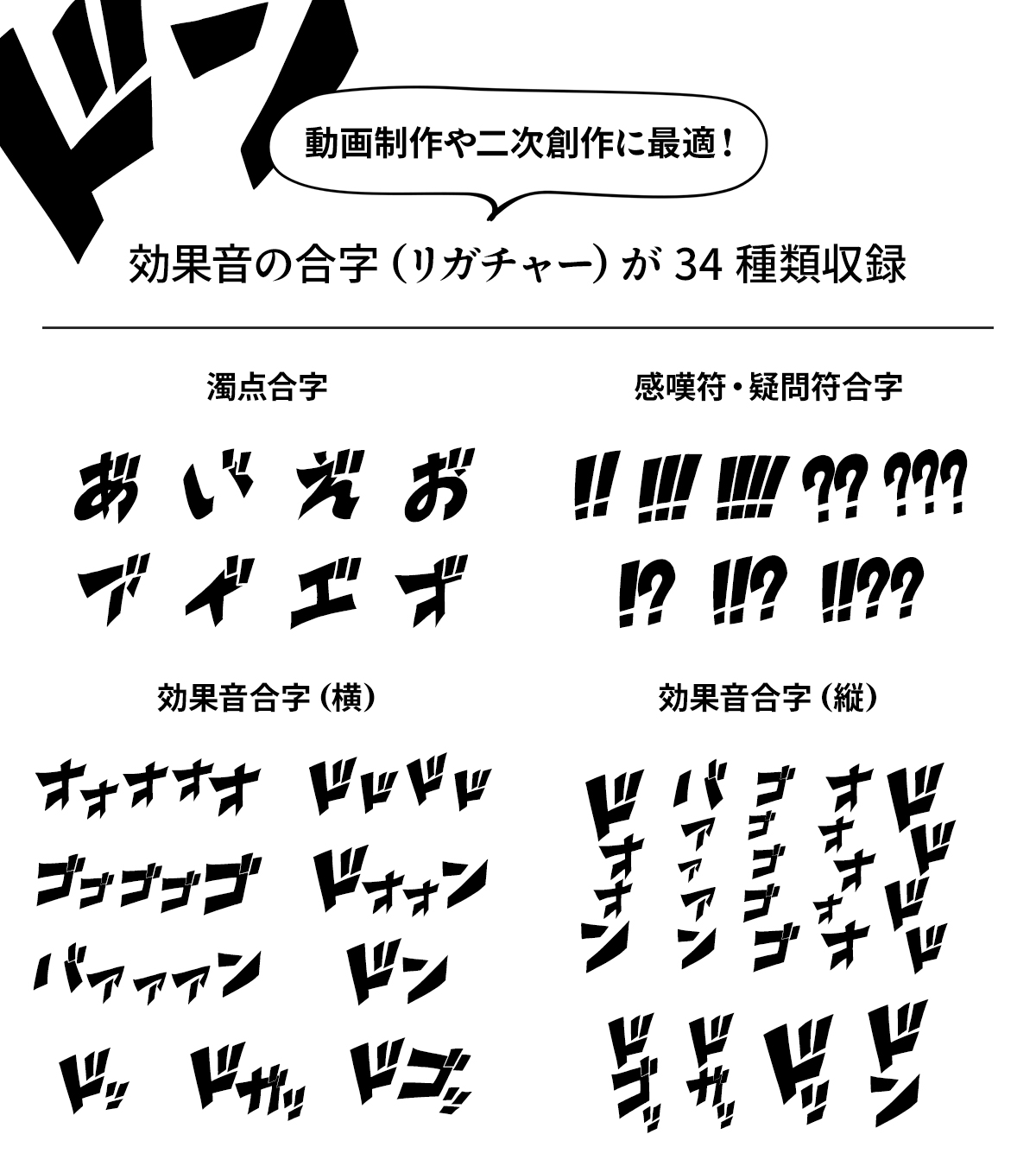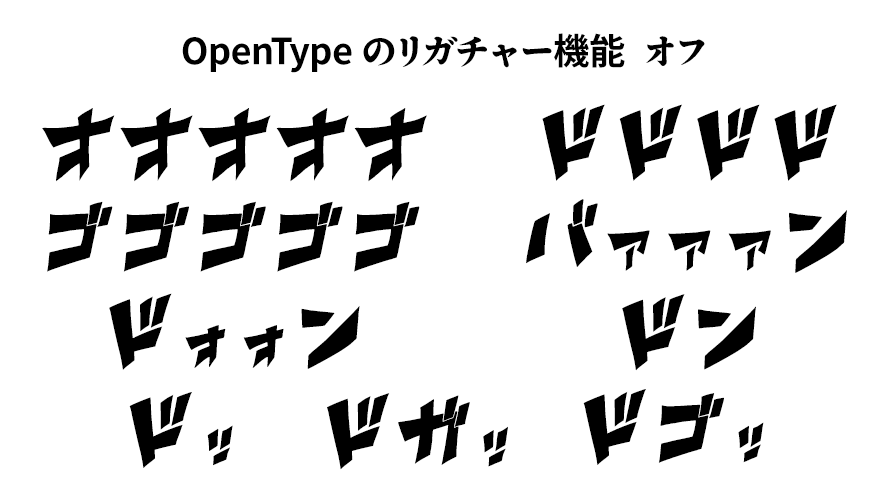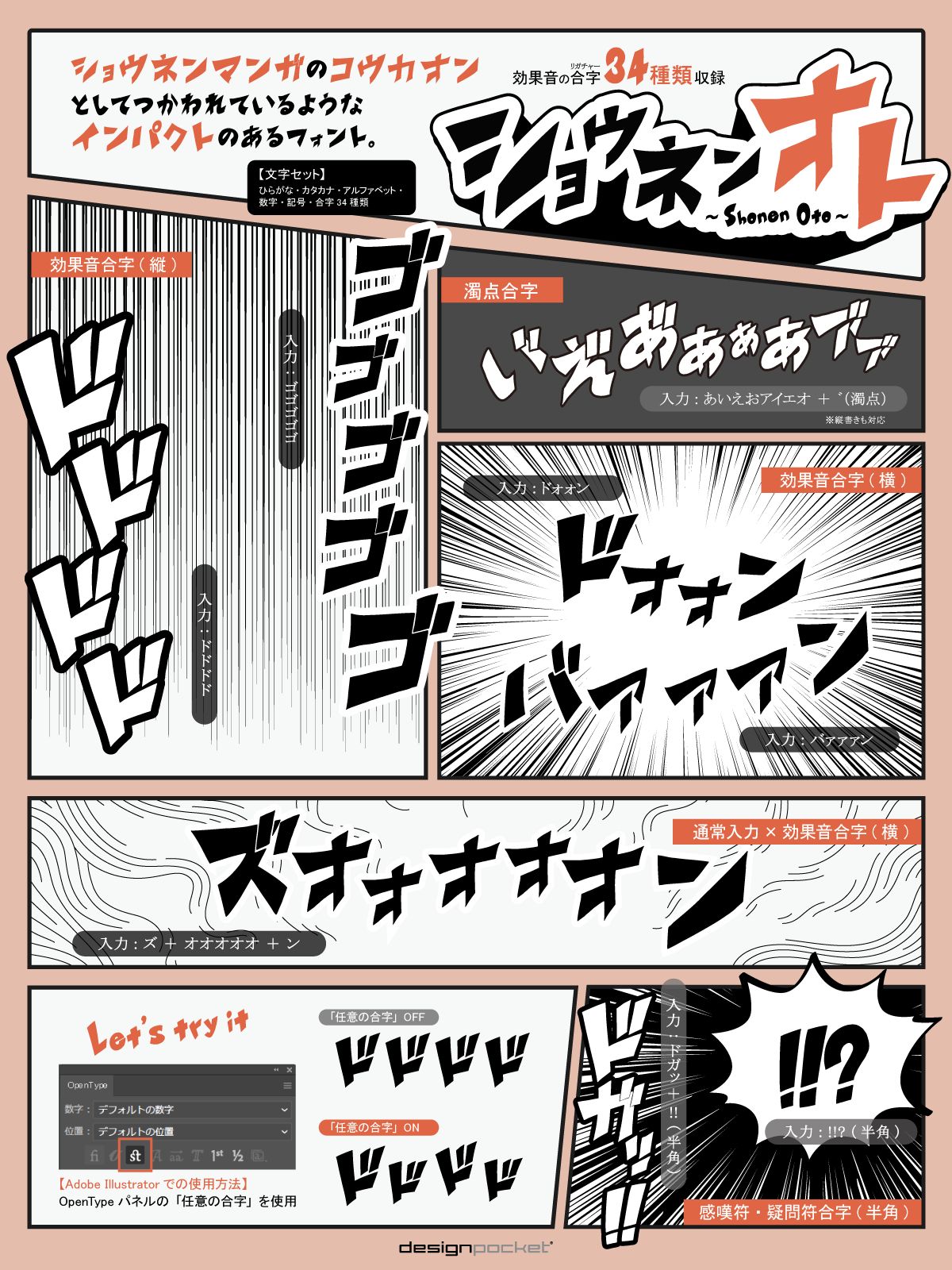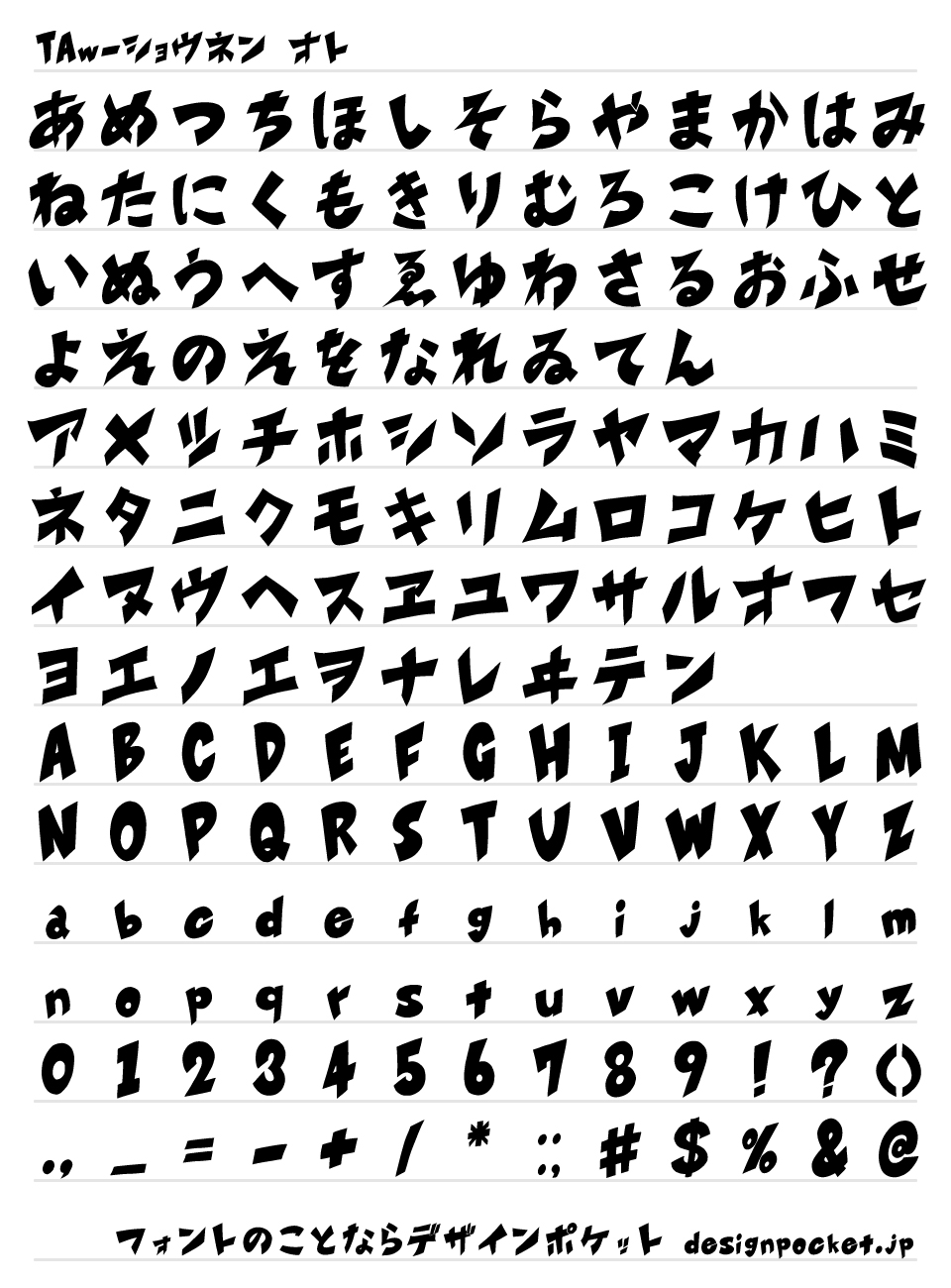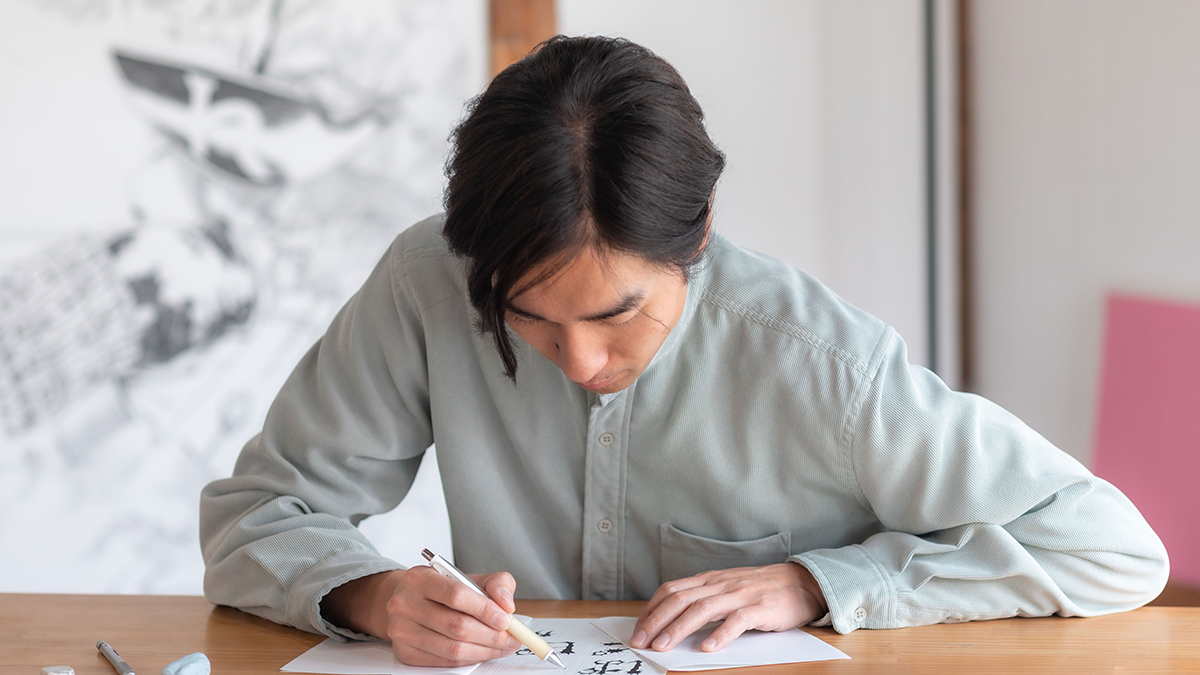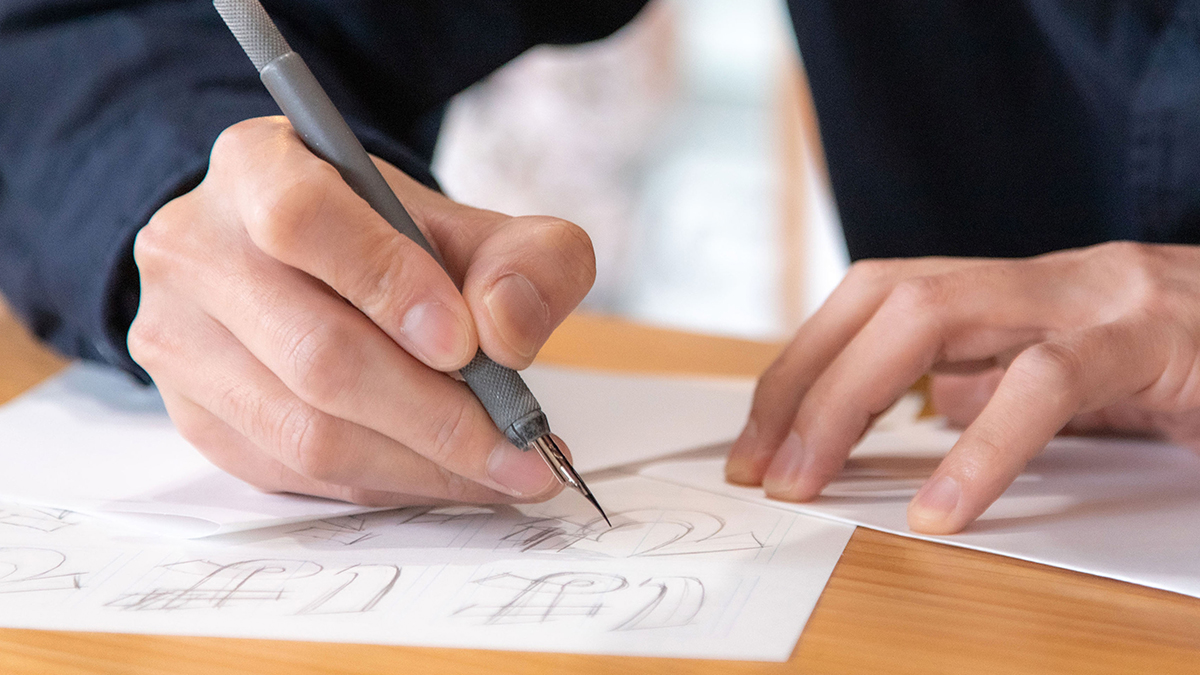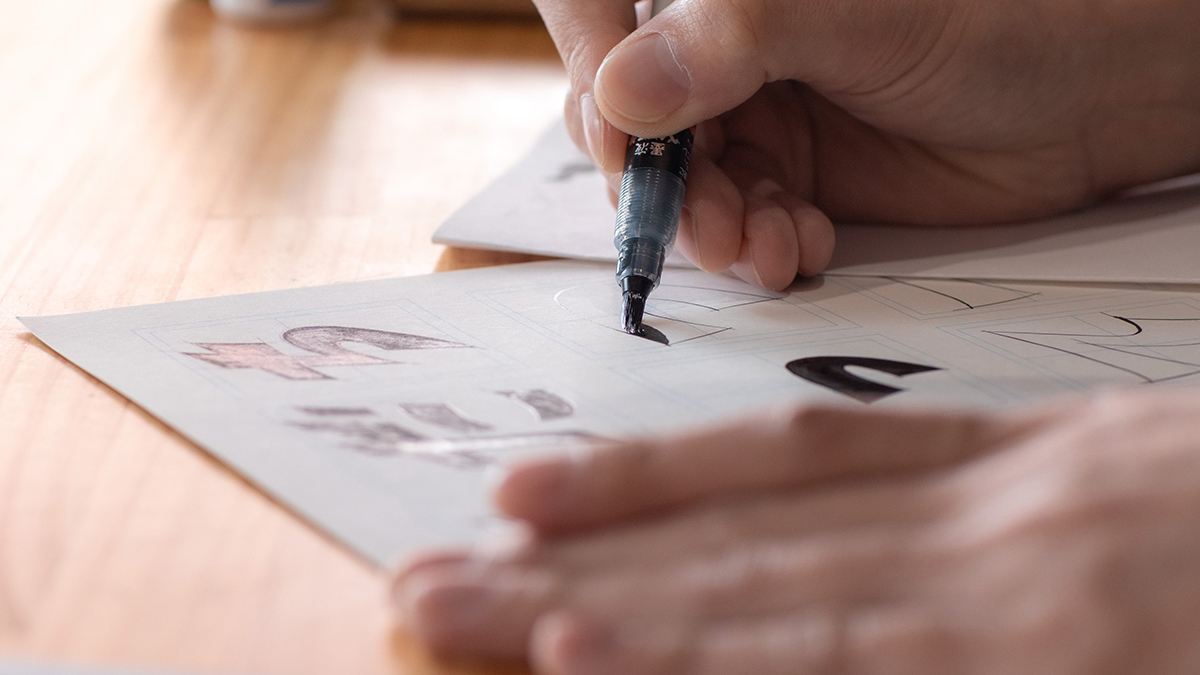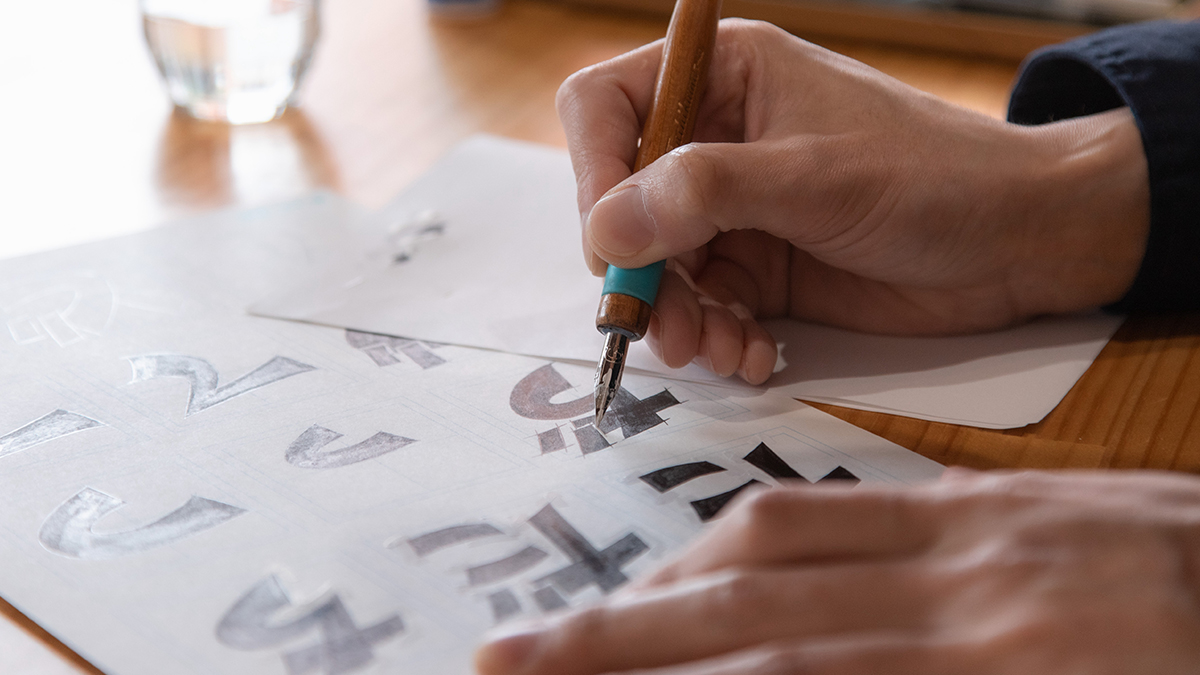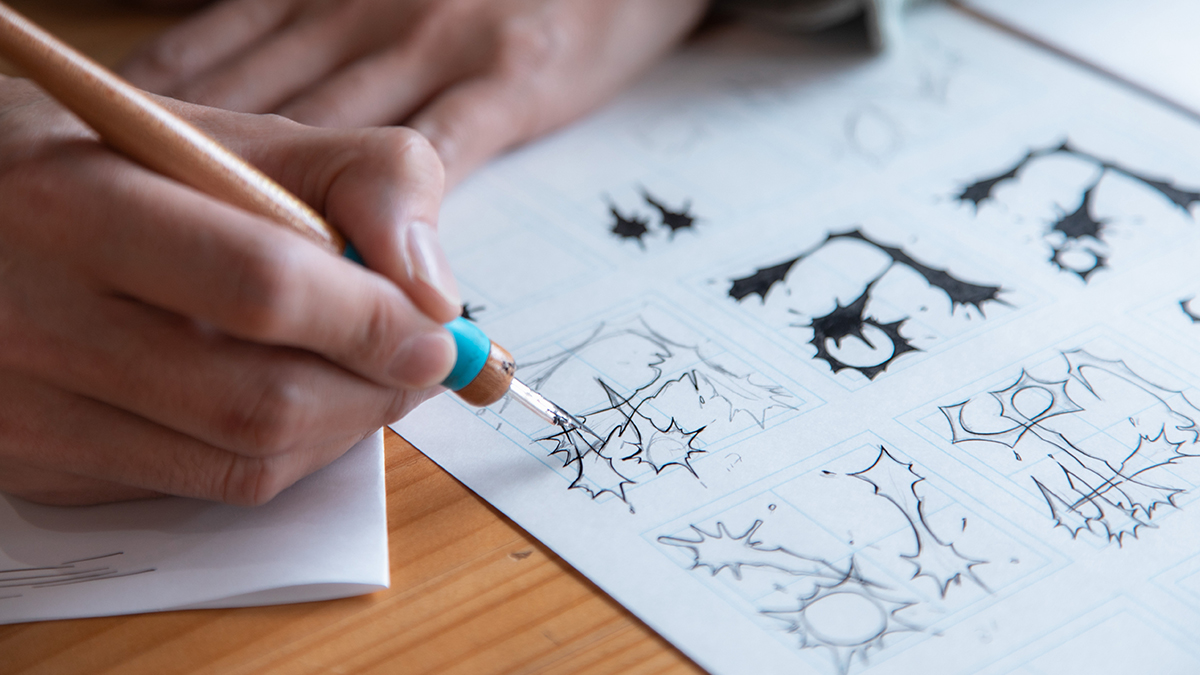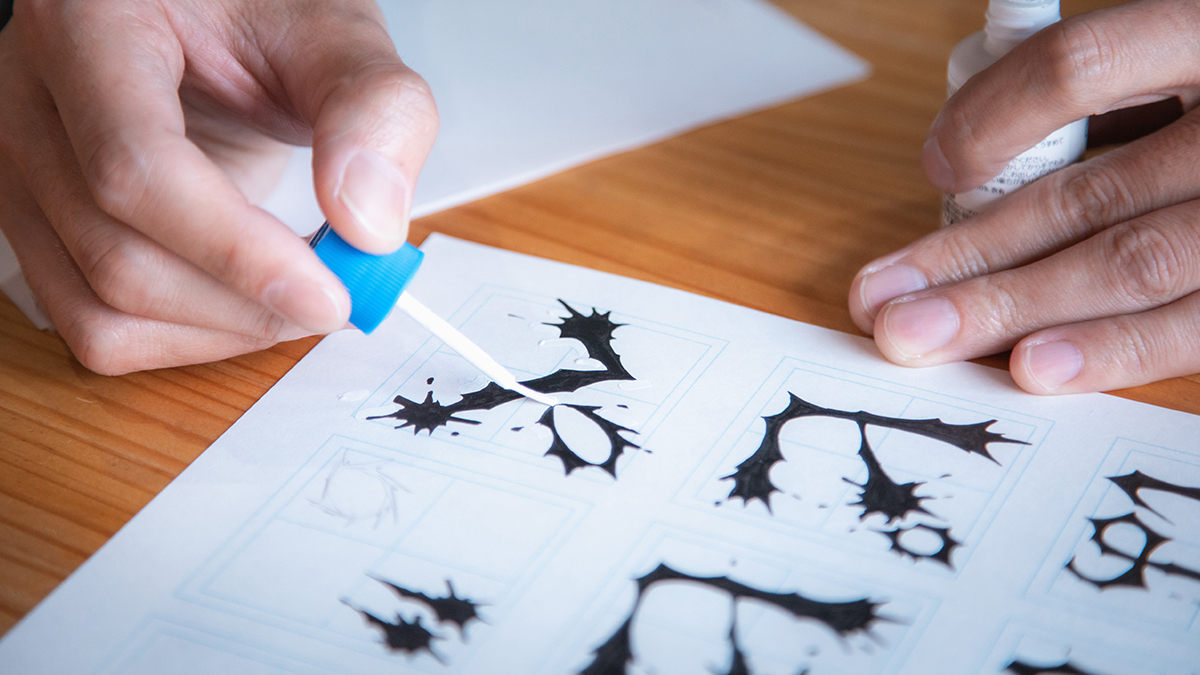
少年漫画のあの“音”を一瞬で再現!感情をダイレクトに伝える効果音フォント ショネン オト Shonen oto
少年漫画のあの“音”を一瞬で再現!効果音書体「ショウネン オト」
「ドガッ!バァァァン!ゴゴゴゴゴ…」少年漫画でおなじみのあの効果音や濁点、感嘆符の表現をリガチャ(合字)機能で一瞬に再現できるフォント「ショウネン オト」。
画像や動画で、こんな効果音を入れたいのに…フォントが普通すぎて雰囲気が出ない?そんなあなたにぴったり。
このフォントなら、入力するだけで少年漫画の効果音風デザインが即完成。手描き風のダイナミックなフォルム&リガチャ(合字)機能で、よりリアルな表現が可能。
動画のテロップやサムネ、漫画制作、SNS投稿など、アイデア次第で使い方は無限大。効果音フォントで、作品の「熱量」を一気にアップ!
「ショウネン オト」の概要
TAw ショウネン オト
効果音フォント ショネン オト 書体見本
ひらがな・カタカナ・アルファベット・数字・記号
効果音に適した合字34種類 / 392文字
「ショウネン オト」とは?
漫画家としても活動していたデザイナーが作った、打つだけで効果音が完成するフォント
効果音フォント ショネン オト 制作者 吉嶺良則さん
「ショウネン オト」は、兵庫県のデザイン事務所MUONの代表である吉嶺良則さんが手がけた効果音フォントです。「下描き」「ペン入れ」「ベタ・ホワイト」とアナログでのマンガ制作の流れに沿って一文字ずつデザインされており、文字を打つだけで手描きのような迫力と臨場感をそのまま再現可能です。
「ショウネン オト」を作ろうと思ったきっかけ
効果音フォント ショネン オト 制作風景1
もともと「ドドドドド」などの効果音文字が欲しいと考えていました。
ウェブフォントジャパン(株)代表 片岡さんが登壇したトークイベントで、フォント制作について話を聞き、「フォントって面白そう!」と感じたことがきっかけです。
音と一致する文字が市場にほとんど存在しないことに気づき、ニーズがあると確信しました。効果音フォントが漫画の表現に大きく貢献できると考えています。
「ショウネン オト」のこだわりのポイント
効果音フォント ショネン オト 制作風景2
手描き感を大事に
少年漫画の効果音に合う、元気で躍動感のある形状を追求。
印刷時の見栄えを考慮し、アナログ感を残す。
線の揺らぎや筆の運びを活かし、デジタルでは出せない味を出す。
収録する文字(合字含む)の選択と、配置やデザインのこだわり
「ドン」「ドドド」など、多くの人がイメージしやすい形に厳選。
文字を単に並べるのではなく、配置による多様な表現を追求。
記号や三点リーダー(…)なども、漫画の表現に合わせてデザイン。
少年漫画の世界観に寄せる工夫
漫画では使わない文字も、世界観に合わせてデザイン。
効果音としてだけでなく、文字として違和感なく使えるバランスを意識。
吉嶺さんが気に入っているところ
効果音フォント ショネン オト 制作風景3
フォントデータ化したときの統一感
文字の勢いを損なわず、フォントとして成立していることを実感した。
効果音としてだけでなく、タイトルやロゴにも応用できる点。
シリーズ展開の可能性
「ショウネン オト」だけでなく、例えば「ホラーオト」「バトルオト」「魔法オト」などのバリエーション展開を考えている。
これにより、ジャンルごとの使い分けが可能になり、フォントの魅力がさらに広がる。
アナログならではの味
筆の運びや修正ペンでの微調整など、デジタルでは表現しきれない要素が残せたこと。
「ショウネン オト」の特徴
リガチャ(合字)機能搭載で、自然な濁点や文字の変化が可能
効果音フォント ショウネン オト 特徴
リガチャ機能により、「あ゛」のような濁点合字や感嘆符・疑問符合字、効果音合字も横書きと縦書きタイプ、すべて合わせて34種類収録。文字の流れも自然に変化し、まるで漫画のコマから飛び出したような仕上がりに。
リガチャ (合字) 機能とは?
効果音フォント ショウネン オト リガチャー機能
リガチャ (合字) 機能とは、OpenTypeフォントに搭載されている機能であり、特定の文字の組み合わせを自動的に合体させて、より自然な形に変えてくれる機能です。
欧文フォントではよく使用される機能で、例えば「fi」という文字の並びの場合は「f」と「i」が一つになった合字に置き換えて見た目を調整し美しく見せてくれます。
「ショウネン オト」では、上記の図のように「ドドドド」「ドゴ」「あ゛」などを入力すると、フォントが勝手に最適な形に変えてくれます。